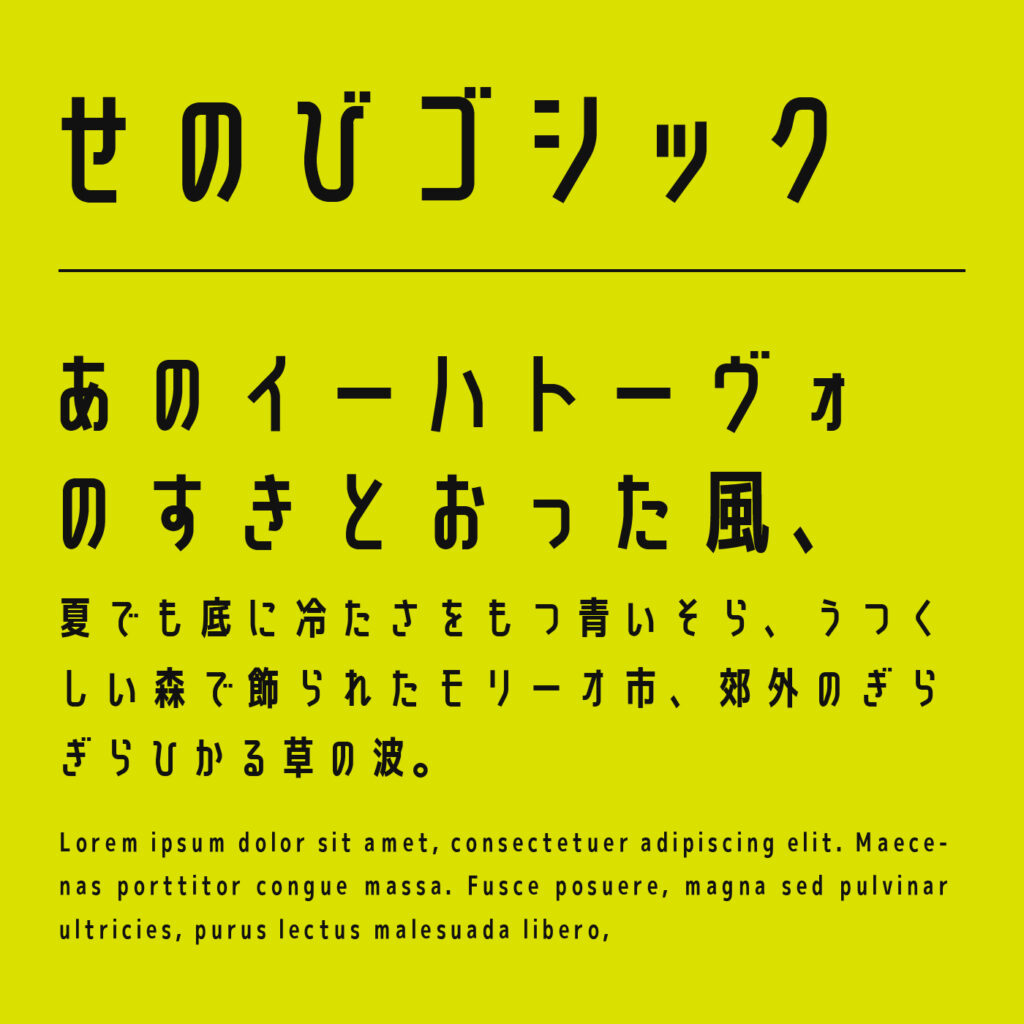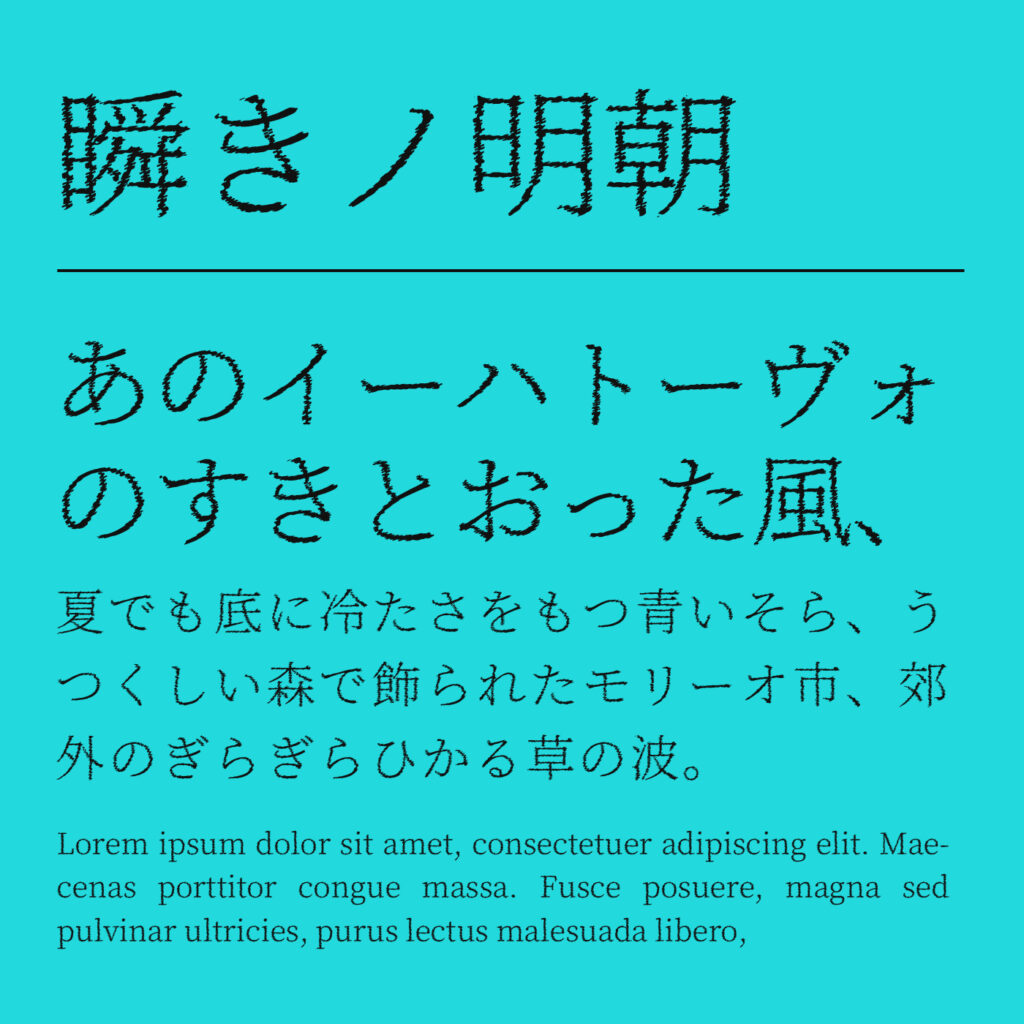
「プラネタリウム・星空」にぴったりな日本語フリーフォント
星空のデザインは、星を散らすだけでは印象が決まりません。細い明朝フォントなら静かな夜に、直線的なゴシックフォントなら宇宙を探る科学的なイメージに近づきます。プラネタリウムの投影番組や星空観察会では、内容に合わせた使い分けが大切です。
今回は、星のきらめきを感じさせるタイトル用から、星座の解説や上映案内に使いやすいものまで、日本語フリーフォントを15個紹介します。暗い背景に細い文字を置く場合は、画面や印刷で線が消えないかも確認して選んでください。
星のきらめきと夜の静けさに合わせるフォント
白光明朝
収録文字ひらがな・カタカナ・漢字・英字・数字・記号
おすすめの場面星空コンサートの告知・投影番組のタイトル
鋭い線と星の装飾で、夜空を印象づける
白光明朝は、細い横線と鋭い輪郭が特徴のフォントです。一部の文字に見られる星の装飾も、プラネタリウムの特別番組に合わせやすい要素です。ただし、どの言葉にも同じ装飾が現れるわけではありません。使うタイトルを組んで確認し、細い線が背景に埋もれない大きさで配置すると、このフォントのきらめきが活きます。
五月雨明朝
おすすめの場面静かな星空映像・夜の観察会ポスター
余白を広く取り、静かな夜を見せる
五月雨明朝は、細く軽やかな線を持つフォントです。星の写真に短いタイトルを添えると、満天の星を邪魔せず穏やかな印象をつくれます。星粒の多い場所には文字を重ねず、背景に空きを確保しましょう。プラネタリウムの案内をすべて細いフォントにするのではなく、情緒的なコピーに役割を絞ると効果的です。
瞬きノ明朝
おすすめの場面流星群の告知・光をテーマにした映像タイトル
残像のような表情を、短い見出しに
瞬きノ明朝は、横方向に揺れた残像のような加工を持つフォントです。流星や光の変化をテーマにしたビジュアルで、静止した文字に動きの印象を加えられます。星座名を細かく並べる用途よりも、一つの短い番組名を大きく扱う場面向きです。装飾を増やしすぎず、補足は素直なフォントで組むと輪郭の面白さが伝わります。
流線形
おすすめの場面星の軌跡を扱う写真展・横組みの宇宙番組名
斜めの流れを、夜空の軌跡と重ねる
流線形は、傾きを持つ明朝系フォントです。星の軌跡や月の移ろいを扱う横組みのコピーに合わせると、時間が流れるような印象を添えられます。文字自体の傾斜を活かし、さらに強い変形を加えないほうが形を保ちやすくなります。解説文用のフォントとは分けて、タイトルの一行に静かな動きを持たせてみてください。
しっぽり明朝
おすすめの場面星にまつわる物語の投影番組・記念パンフレット
やわらかな明朝で、星の物語へ誘う
しっぽり明朝は、線の接点に温かみがあり、物語を感じさせるフォントです。星座にまつわる話や季節の夜空を紹介する番組で、硬い科学情報とは異なる情緒を添えられます。タイトルと短い導入文を同じフォントでまとめても、太さを変えれば読みどころができます。星の写真を大きく見せた紙面にも合わせやすい候補です。
はんなり明朝
おすすめの場面七夕の星空イベント・月をテーマにした展示
しなやかな仮名で、季節の夜を表す
はんなり明朝は、やわらかな筆の流れを感じるフォントです。七夕や月見など、日本の季節と夜空を結ぶ企画に使うと、落ち着いた趣が生まれます。和風の装飾を多く加えなくても、かなの表情だけで雰囲気を整えられます。日時や会場は別のゴシックフォントにして、季節感を伝える言葉を引き立てる使い方がおすすめです。
源暎こぶり明朝
おすすめの場面星座物語の冊子・朗読番組の配布資料
小ぶりな仮名で、物語をゆっくり読ませる
源暎こぶり明朝は、仮名を小ぶりに整えた文章向けのフォントです。星座の物語を読ませる冊子や、朗読番組の補助資料に向いています。星空らしさを過剰な飾りで表すのではなく、文章の静かなリズムを支えられます。大きな番組名には別のフォントを使い、読ませる段落でこのフォントの落ち着きを活かしましょう。
夜永オールド明朝
おすすめの場面縦組みの星空エッセイ・企画パンフレット
縦組みで、夜の余韻を伝える
夜永オールド明朝は、縦組みを意識して調整されたオールドスタイルのフォントです。夜空の体験を綴るエッセイや、縦組みのリーフレットに取り入れると落ち着いた印象になります。名前だけで星空向けと考えるのではなく、文章の組み方に合う点が選ぶ理由です。短い横組みの時刻表示には、別の情報用フォントを組み合わせると安心です。
Noto Serif
おすすめの場面天文展示の解説・星空写真集
明朝の端正さで、写真と知識をつなぐ
Noto Serifの日本語版は、星空写真に添える説明を端正にまとめたいときに使えるフォントです。情緒的な写真と、星の名前や観測についての文章を落ち着いてつなげます。日本語版を選び、特殊記号や単位は実際に入力して確認しましょう。長い解説は行長を抑え、見出し用フォントと大きさの差をつけると読みやすくなります。
せのびゴシック
おすすめの場面天文イベントの縦長ポスター・観測企画の見出し
細身の文字で、すっきりした宇宙感を
せのびゴシックは、縦にすっと伸びた印象を持つフォントです。星空写真を広く見せながらタイトルを置きたい縦長の告知物に向いています。本文まで細身の文字で詰め込むと読みにくくなるため、見出しで使うのが取り入れやすい方法です。字間を少し確保すれば、無機質なフォントの表情と夜空の広がりを両立できます。
源直ゴシック
おすすめの場面宇宙科学の展示タイトル・観測機器の紹介パネル
直線的な文字で、宇宙を科学の視点から
源直ゴシックは、曲線を直線的に見せる加工が特徴のフォントです。宇宙をロマンだけでなく技術や観測のテーマで伝える展示に合います。観測機器の写真と短い見出しを組むと、硬質な印象がまとまります。精密な数値や長い説明は標準的なフォントに分け、デザインの主張はタイトルに集めると情報が整理されます。
モノマニアック(Monomaniac)
おすすめの場面カタカナの宇宙企画名・子ども向け番組告知
丸く太い長体で、宇宙探検を楽しく
モノマニアックは、丸みのある太い線と細身の字形が特徴のフォントです。「プラネット」などカタカナ中心の企画名で、未来的で親しみやすい表情をつくれます。漢字は収録されていないため、タイトルの内容に合わせて選んでください。説明用の日本語フォントを別に用意すると、楽しいタイトルと実用的な案内を無理なく共存させられます。
でんきチップ